9 sitios web para encontrar las mejores fuentes tipográficas
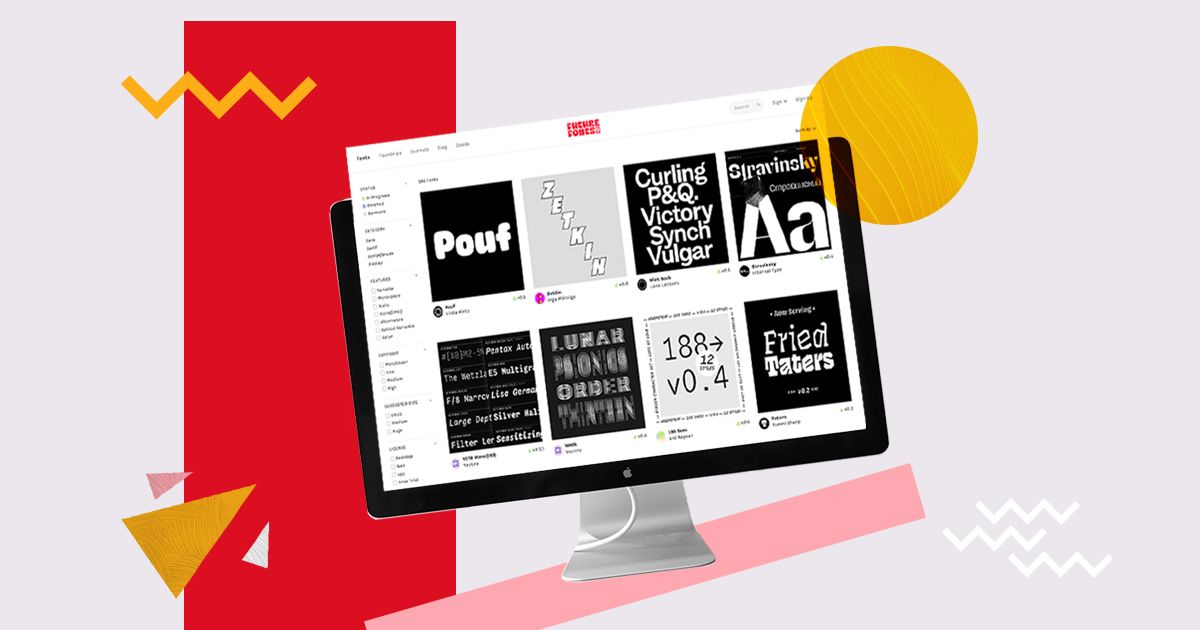
Descubre las mejores tipografías para inspirarte y componer tus próximos proyectos gráficos creativos
Elegir la tipografía adecuada es un paso importante para definir el tono y la personalidad de un proyecto.
Después de todo, las tipografías ofrecen infinitas posibilidades de comunicación y expresión, además de ayudar a definir diversos aspectos de un diseño.
Una buena fuente puede sintetizar muchos valores en un único concepto que, posteriormente, se trasladará a una imagen gráfica capaz de causar emoción.
Álvaro Franca (@alvaroefe), diseñador gráfico y diseñador de lettering, es cofundador de Naipe Foundry, donde trabaja con clientes como TV Globo, Sony Music y Descomplica.
Para ayudarte a encontrar buenas referencias y fuentes tipográficas, Álvaro comparte a continuación una lista comentada de los mejores sitios web para descubrir nuevas fuentes y diseños.
El diseño de la identidad de una marca es el lenguaje visual utilizado entre una empresa y su público. Cuando los elementos visuales de una marca están pensados a través de la tipografía, es posible crear una experiencia más personal y completa para el cliente.
En este tutorial, el diseñador te enseña a definir la tipografía ideal para tu marca mediante ejemplos prácticos, teniendo en cuenta elementos como la personalidad y el propósito.